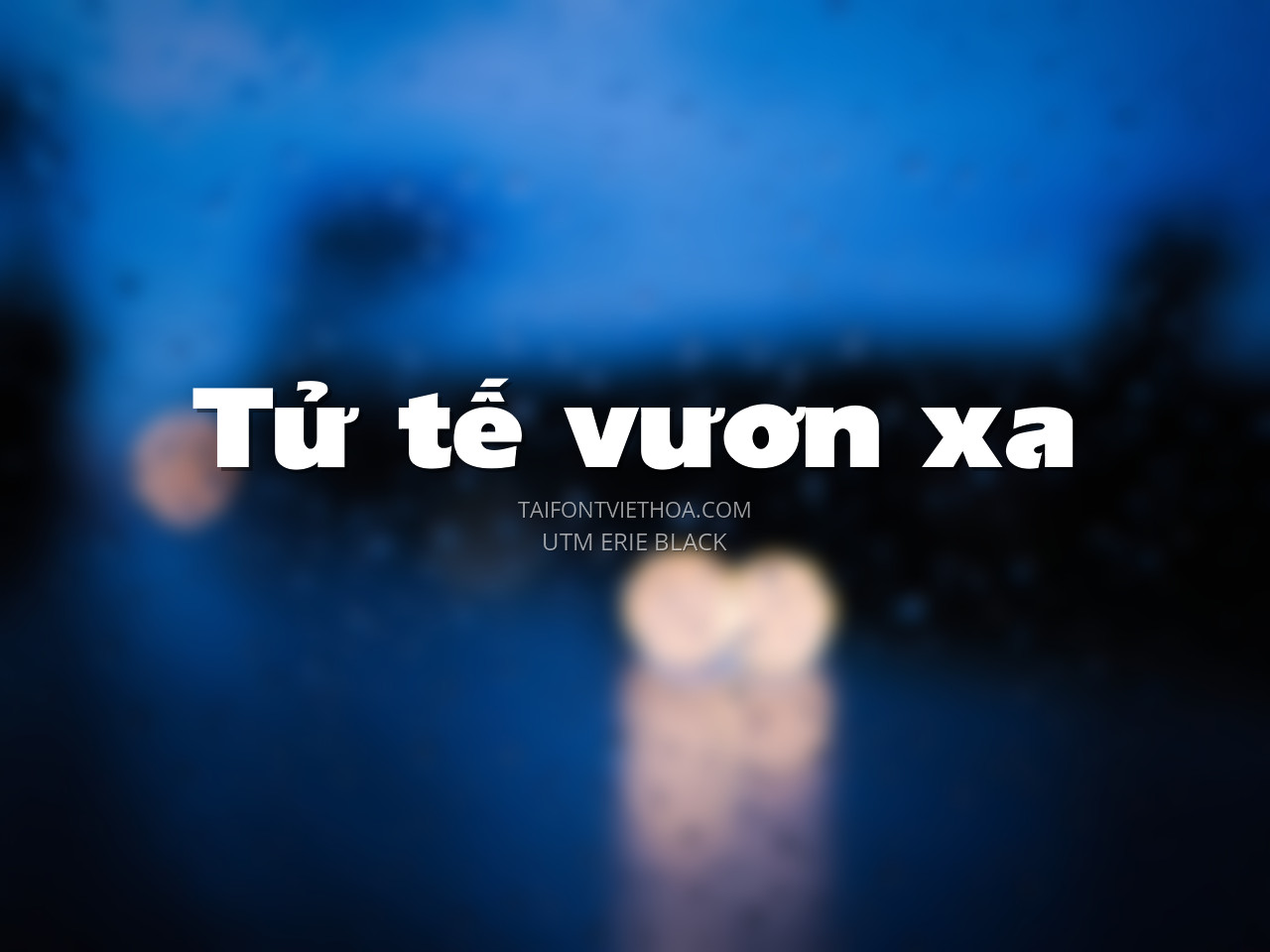
Font việt hóa UTM Erie Black
Giới thiệu về font UTM Erie Black
UTM Erie Black là phiên bản Việt hóa của font Erie Black – một kiểu chữ display đậm nét và cá tính, được thiết kế để tạo điểm nhấn mạnh mẽ trong các dự án thiết kế. Font gốc nổi bật với các nét chữ dày, vuông vức và thiết kế chắc chắn, rất phù hợp cho tiêu đề, bảng hiệu và các thiết kế cần sự nổi bật và ấn tượng. Phiên bản Việt hóa đã được hoàn thiện để hỗ trợ đầy đủ tiếng Việt cùng hơn 100 ngôn ngữ khác, mở rộng khả năng ứng dụng trong các dự án sáng tạo đa dạng.
Font UTM Erie Black được taifontviethoa.com sưu tầm và lựa chọn kỹ lưỡng nhằm phục vụ cộng đồng thiết kế Việt Nam. Phiên bản Việt hóa giữ nguyên phong cách mạnh mẽ và cá tính của bản gốc, đồng thời tối ưu khả năng hiển thị tiếng Việt, rất phù hợp cho các dự án thương hiệu, quảng cáo và truyền thông sáng tạo.
Đặc điểm thiết kế và ứng dụng của UTM Erie Black
UTM Erie Black sở hữu cấu trúc display với các nét chữ dày, vuông vức và rõ ràng. Font có thiết kế chắc chắn, dễ đọc và tạo hiệu ứng thị giác mạnh mẽ, rất phù hợp cho tiêu đề, logo và các thiết kế cần sự ấn tượng. Font còn được trang bị nhiều ligature và glyph thay thế giúp tăng tính linh hoạt trong thiết kế.
Font thích hợp sử dụng trong thiết kế poster, bảng hiệu, nhận diện thương hiệu, quảng cáo và các dự án truyền thông đa phương tiện. Các ngành nghề phù hợp gồm: giải trí, công nghệ, thời trang, sự kiện và truyền thông sáng tạo.